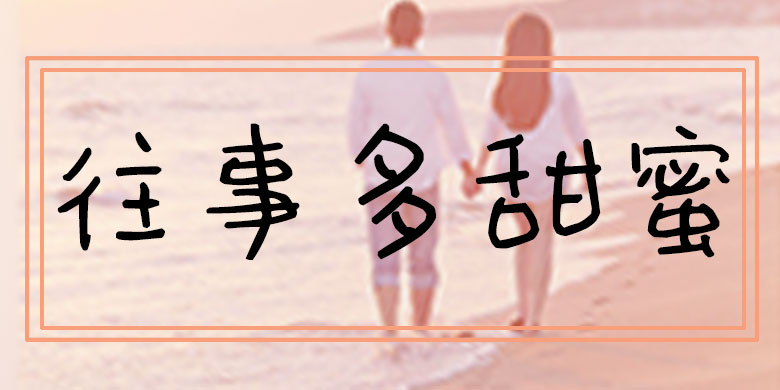
方正手迹-往事多甜蜜
方正手迹-往事多甜蜜,这款字体结构工整、笔画清晰,兼顾美观与易读性,适用于标题、正文、海报、包装、LOGO 等多种场景。字形优雅稳定,风格百搭耐看,适配日常排版与创意设计,让文字呈现更舒适、更具质感。方正手迹-往事多甜蜜一笔一画,皆是细节,以均衡的比例、流畅的线条打造舒适视觉体验,字形端正大气,风格简约现代。无论是商业设计、品牌宣传还是日常排版,都能轻松驾驭,让文字更有格调与力量。方正手迹-往事多甜蜜字体下载。
字形可爱,笔画夸张,采用变形手法,参差并极具张力。线条简洁,转折圆滑,简洁流畅,单纯可爱。笔画的跃动感极强,给字体带来了生命力,显得朝气蓬勃,可爱动人。适用于少年儿童类的书刊、品牌广告和产品包装设计,以及社交网络的个性化用字。